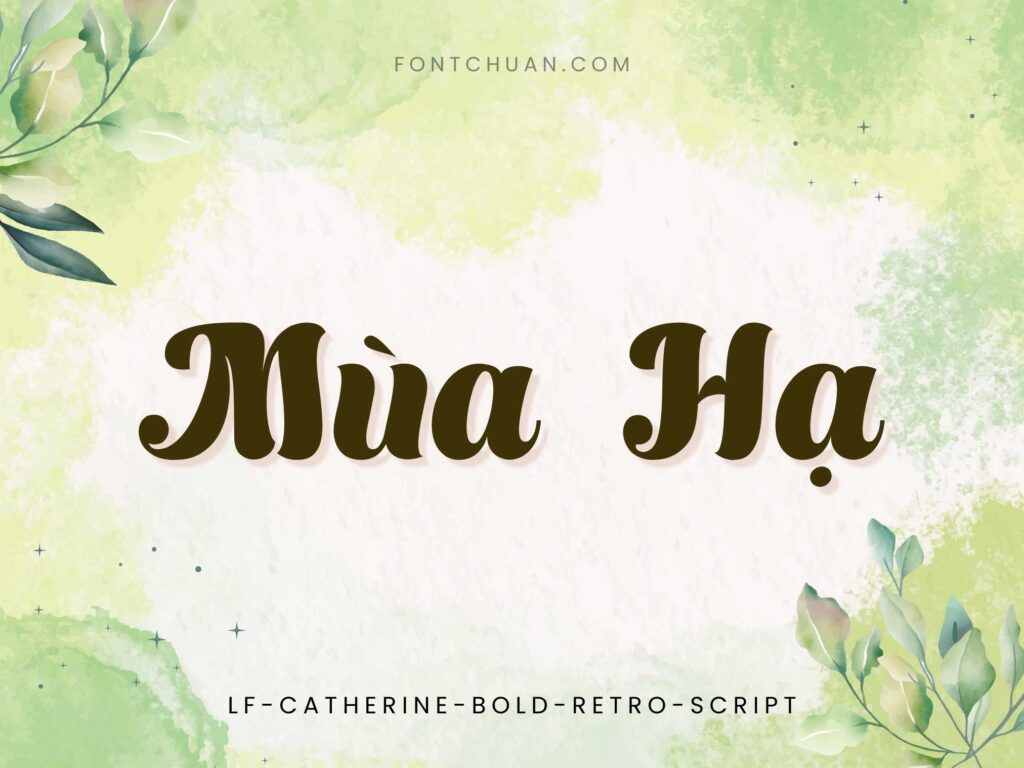
Font Lf Catherine Bold Retro Script Việt Hóa
Tác giả Font: Cruzine
Việt hóa bởi: Lengnef
Catherine Bold Retro Script là một phông chữ script đậm nét, mang phong cách cổ điển và retro, được thiết kế bởi Peter Olexa. Phông chữ này kết hợp sự thanh lịch và sáng tạo, tạo nên một phong cách độc đáo cho các dự án thiết kế hiện đại hoặc mang hơi hướng hoài cổ. Với các đường nét tròn trịa và phong cách vintage, Catherine phù hợp cho các dự án thiết kế đòi hỏi sự tinh tế và cổ điển. Phông chữ này cung cấp nhiều ký tự thay thế và ligatures, giúp tạo ra các thiết kế logo độc đáo hoặc tiêu đề trang web ấn tượng. Catherine hỗ trợ đa ngôn ngữ, bao gồm cả tiếng Việt, mở rộng khả năng ứng dụng trong các dự án quốc tế.
Phông chữ này phù hợp cho các ứng dụng như thiết kế logo, tiêu đề, thương hiệu lấy cảm hứng cổ điển, biển hiệu và các dự án sáng tạo khác. Catherine cũng có thể được sử dụng như một Font chữ công nghệ, lý tưởng cho các thiết kế liên quan đến giao diện số, website, ứng dụng phần mềm hay tài liệu kỹ thuật, mang lại vẻ hiện đại, gọn gàng và chuyên nghiệp. Về ngành nghề, Catherine đặc biệt phù hợp với lĩnh vực quảng cáo, công nghệ, giáo dục và các ngành nghề cần sự sáng tạo và hiện đại trong thiết kế. Sự linh hoạt và tinh tế của phông chữ giúp nó dễ dàng hòa nhập vào nhiều phong cách thiết kế khác nhau, từ cổ điển đến hiện đại.
Ngoài ra, để mang không khí lễ hội, vui nhộn, Catherine Bold Retro Script lựa chọn lý tưởng để làm Font chữ Halloween với các họa tiết đặc trưng như mạng nhện, dơi và bóng ma, tạo điểm nhấn sôi động cho các sự kiện như lễ hội, sinh nhật, ngày Nhà giáo và Valentine, giúp các thiết kế trở nên nổi bật và độc đáo hơn so với phong cách cổ điển của Catherine.